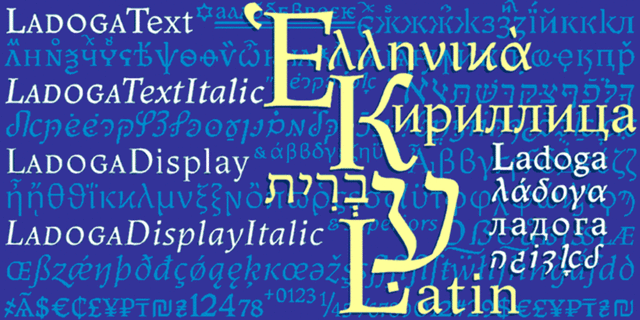
Одна из красивейших советских гарнитур была создана для Отдела новых шрифтов НИИ Полиграфмаш в 1968 году Анатолием Щукиным на основе собственных рисованных обложек и титулов. Это один из первых опытов создания кириллического наборного шрифта в стиле ренессансной антиквы. Стилизация под ширококонечное перо роднит ее с наиболее ранними формами антиквы, связанными с рукописным гуманистическим минускулом. Уникальная по объему цифровая версия прямого и курсивного начертаний Ладоги на основе рисунков Щукина разработана Виктором Хариком для компании ПараТайп. Каждое начертание имеет два варианта – текстовой и титульный и включает как оригинальную версию шрифта, так и более современные варианты рисунка, а также дополнительные и альтернативные знаки, минускульные цифры и капитель. В комплект также входят национальные знаки практически всех современных языков, пользующихся латиницей и кириллицей, знаки древне- и новогреческого алфавита, включая акценты, знаки исторической кириллицы, включая титла, а также знаки еврейского алфавита. Ладога изысканна и красива в крупном кегле как акцидентный шрифт и хорошо читается в мелких текстовых кеглях. Она подходит для художественных, исторических, культурологических, искусствоведческих, религиозных и филологических текстов, в том числе для многоязычных изданий и включения в текст исторических фрагментов в оригинальной орфографии. Гарнитура выпущена в 2010 году.
Ассоциации c начертанием Ladoga Text RegularКачества и характер:
комильфо, старинный, исторический, сказочный, мастерский, художественный, благородный, красивый, выразительный, характерный, прекрасный, гуманитарный, динамичный, фантастичный, острый